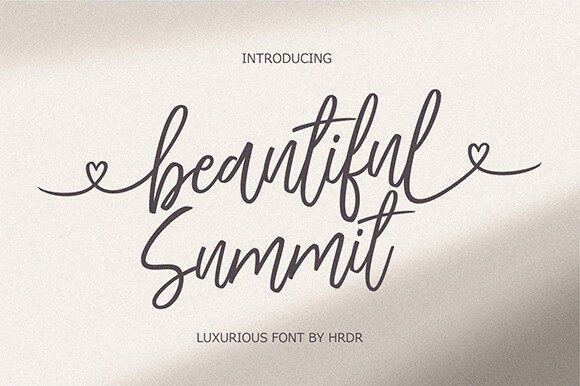
Beautiful Summit
Encontrar los elementos de diseño adecuados puede ser un desafío, pero Beautiful Summit ofrece una colección excepcional que eleva tu trabajo al instante.